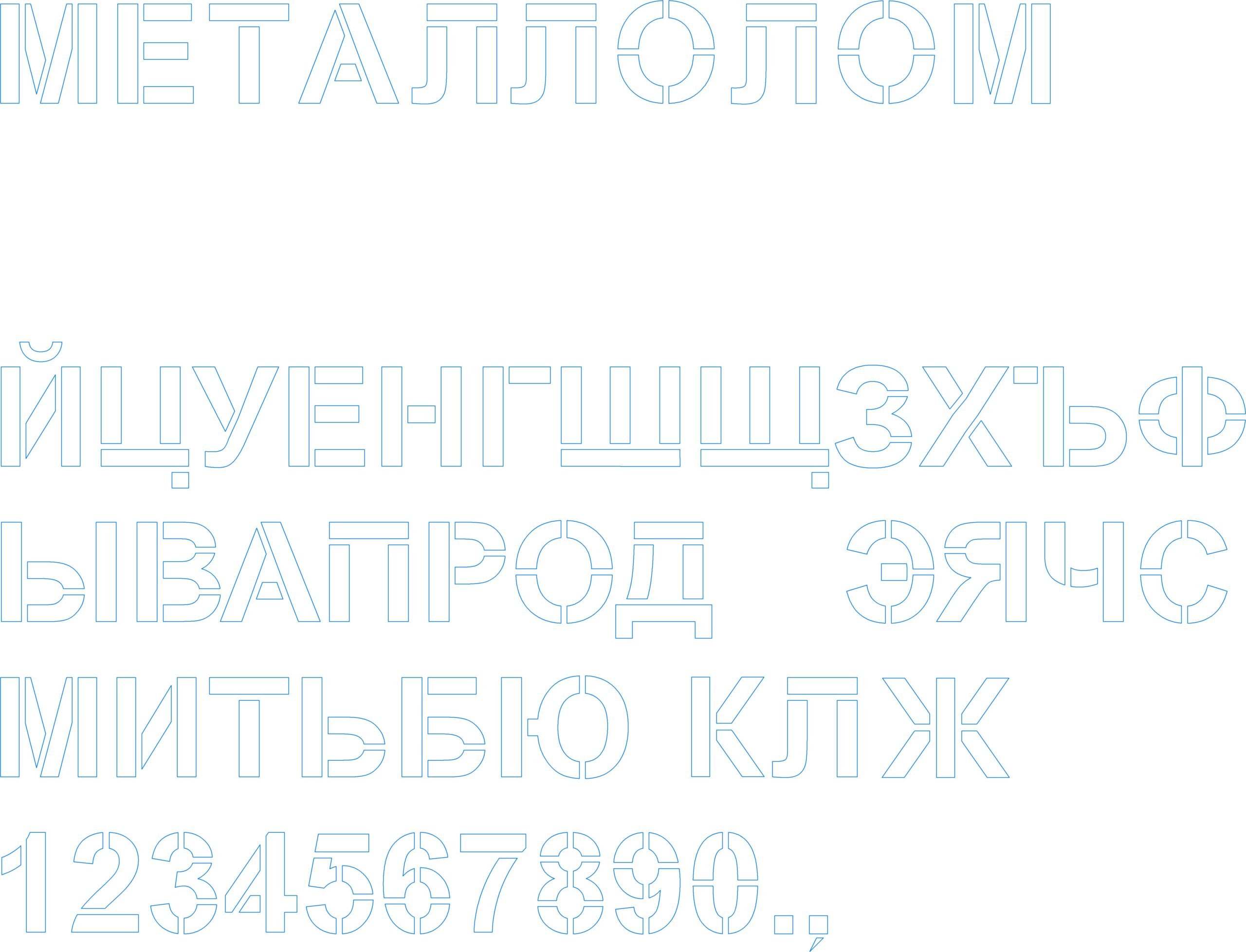
Шрифт для составления трафаретов, используемых для нанесения надписей краской на изделия, тару и т.д. Буквы трафарета копируем, нужный размер получаем путем масштабирования.
Векторный трафаретный шрифт